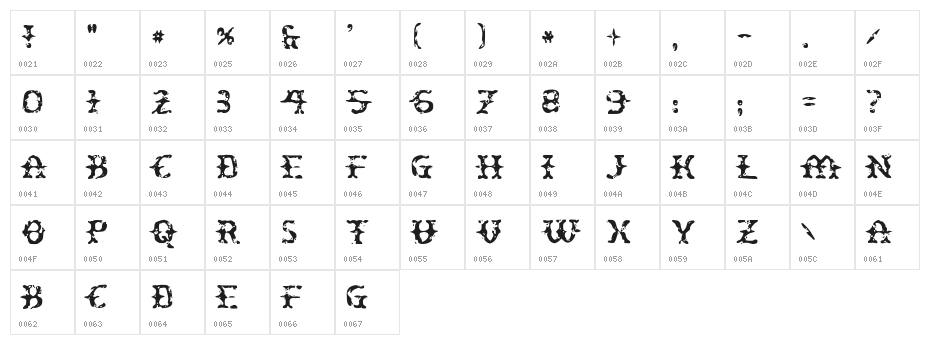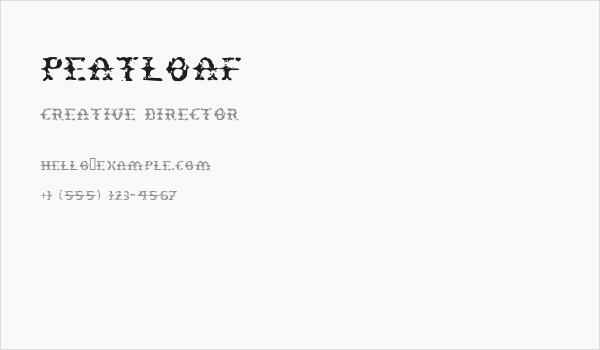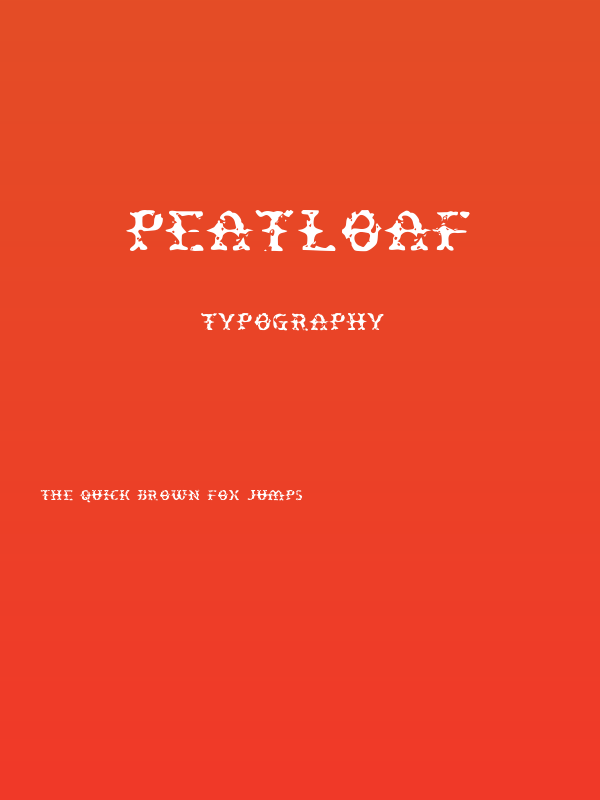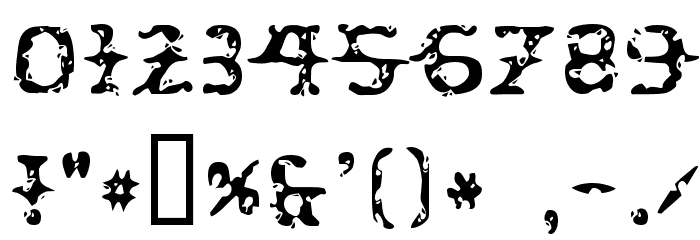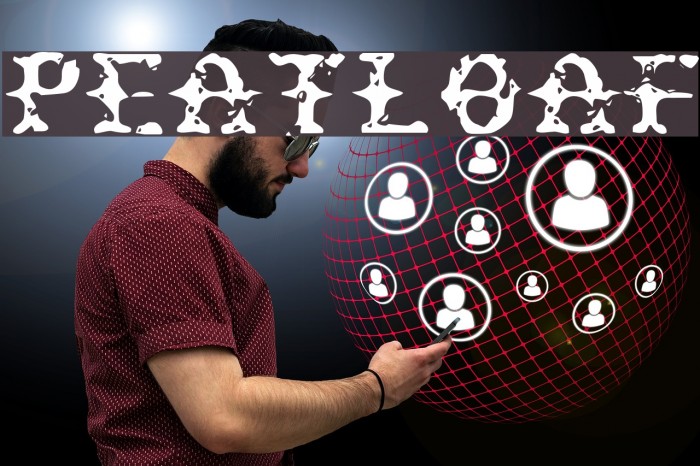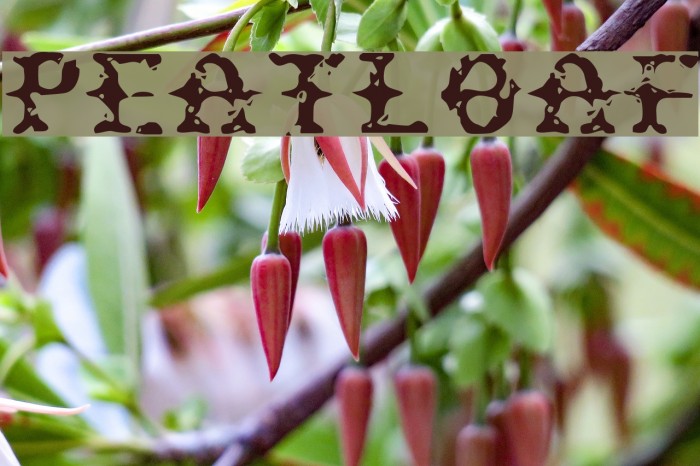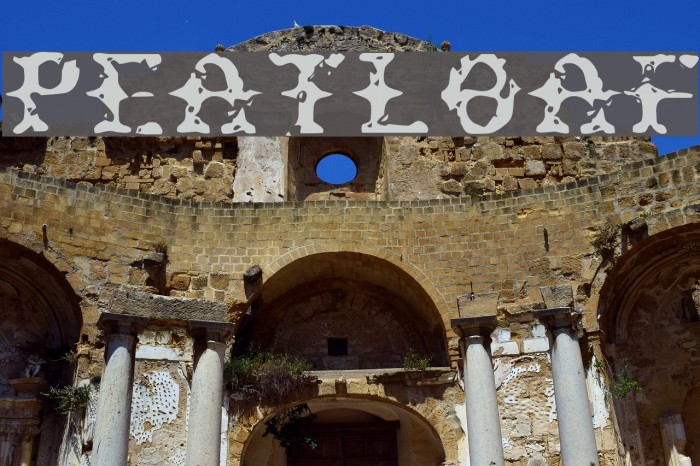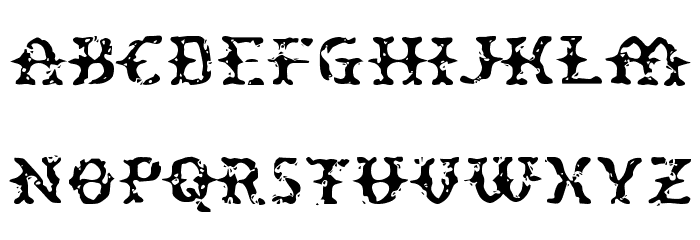
Peatloaf Font
| Gesamtstil | Vintage, Grunge |
| Vorgeschlagene Projekte | Ideal for album covers, posters, branding for edgy or vintage-themed products, and any design needing a bold, distressed look. |